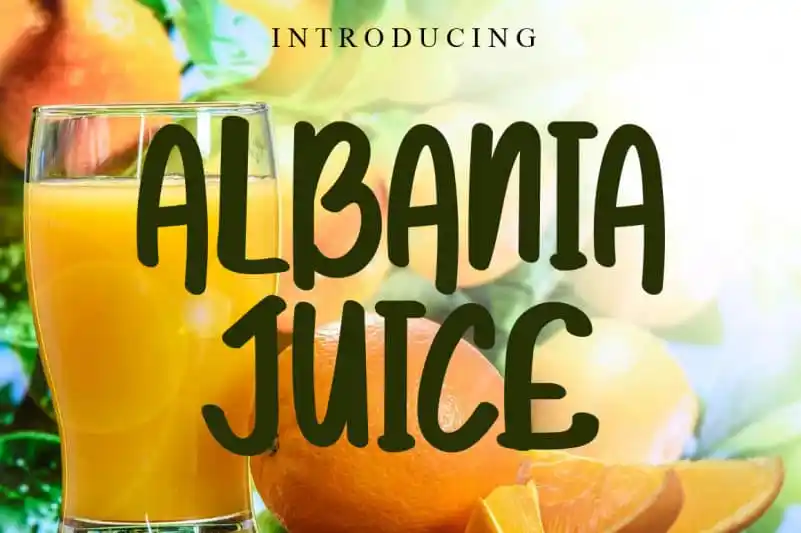
Albania Juce Display Font – Download Grátis
A Albania Juce Display Font é uma elegante escolha para designers que buscam dar vida a seus projetos com um touch natural e relajado. Esta fonte escrita à mão expressa simplicidade, mas não deixa de manter uma forte presença visual, tornando-a imediatamente atraente em qualquer criação. Perfeita para adicionar um toque único e autêntico a projetos digitais ou impressos, ela oferece um estilo casual e envolvente que certamente diferenciará seu trabalho entre outros. Composta de linhas fluidas e traços suaves, o resultado é uma fonte ideal tanto para títulos quanto para textos mais detalhados, garantindo um design harmonioso e agradável aos olhos. Seja para sites, editoriais ou até mesmo logotipos, a Albania Juce Display Font é definitivamente um recurso gráfico que tornará sua identidade visual mais especial e única.